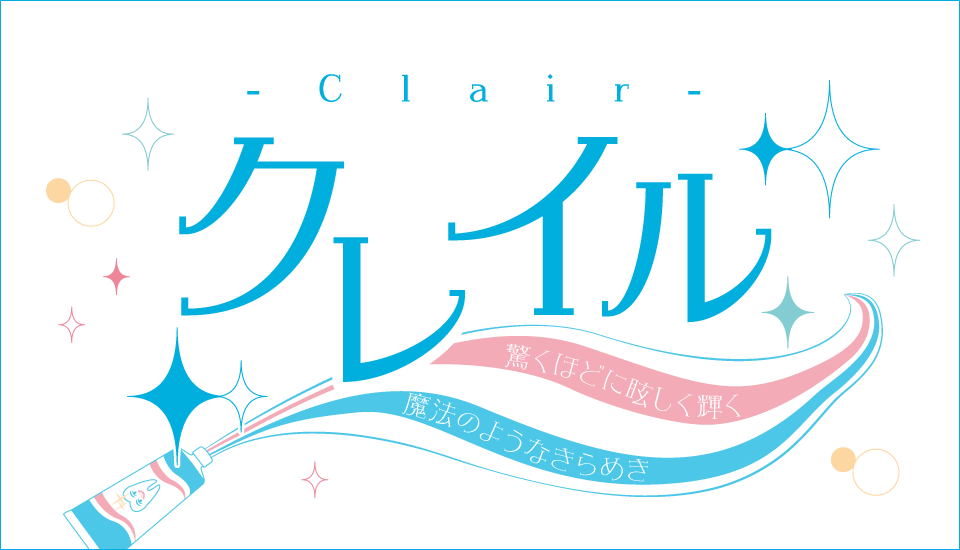
文字にツヤと光沢感を与えるデザイン書体 「モトヤクレイル」
文字にツヤと光沢感を与えるデザイン書体『モトヤクレイル』が登場!
これまでのモトヤにないエレガントな表情を持つデザイン書体「モトヤクレイル」。「清潔感」と「高級感」を持ち合わせ“魔法のようなきらめき”を実現してくれます。
モトヤクレイルとは
エレガントな印象を持つデザイン書体です。クレイルは、これまでのモトヤ書体にはなかった文字の表情として「清潔感」と「高級感」を持ち合わせています。クレイルをご使用いただくことで、媒体がまるで自ら光り輝きだしたかのような、ツヤと光沢感を付与することができ、より魅力的で効果的な表現が可能になります。どんな商品の印象や雰囲気、場面においても「清潔感」や「高級感」は欠かせません。そんな時に、パッとそれらを付与できる“魔法のようなきらめき”を実現してくれるのが、この『クレイル』となります。
※ここでいう表情とは、その文字の持つ印象や、その文字で組まれた文章全体から感じ取ることができる雰囲気のようなものを指しています。
書体の特徴
「清潔感」「高級感」と一言に言ってもそれぞれ性質が異なるので、本来結びつけることは難しいものです。これを文字の印象で結びつけることができれば面白いのではと思い、開発に取り掛かりました。そうした時に「清潔感」からは物を綺麗にピカピカにする印象や、白くて光沢感がある歯という部分から歯科衛生士という印象を、そして「高級感」には高級車のキラキラした眩しいツヤや、手の届かない遠くにある星のような存在という印象を感じました。
この“キラキラまたはピカピカと星や光が瞬くような印象”を文字に付与できないかと思い、よく星のきらめきなどを表現する際に見る「十字光」を参考にし、クレイルにはヘアラインセリフを採用しました。また、単に文字の一部に光の印象を付与するだけでは弱いのではと思い、“手の届かない存在”を強めるために、文字のバランスは全て足長気味にデザインし、あえて重心を高めに設定することで“「美」への意識の高さ”を表現してみました。これがクレイル制作時のこだわりのポイントです。
書体名の由来
書体の特徴でも触れた「清潔感」「高級感」からの“キラキラまたはピカピカと星や光が瞬くような印象”や、文章に「ツヤ」「光沢感」を付与できるという性質から、書体名にはフランス語で「明るい」「光」を意味する『Clair(クレイル)』が案として挙がり、書体のイメージに合っていて音も綺麗だったのでそれを書体名にしました。
使用例
モトヤクレイルは、文字の表情として「清潔感」「高級感」を持ち合わせているため、例えば清掃用品・歯科衛生用品・洗車グッズのパッケージやロゴ、美容室・サロンの看板やキャッチコピーへの使用にも最適です。
書体見本